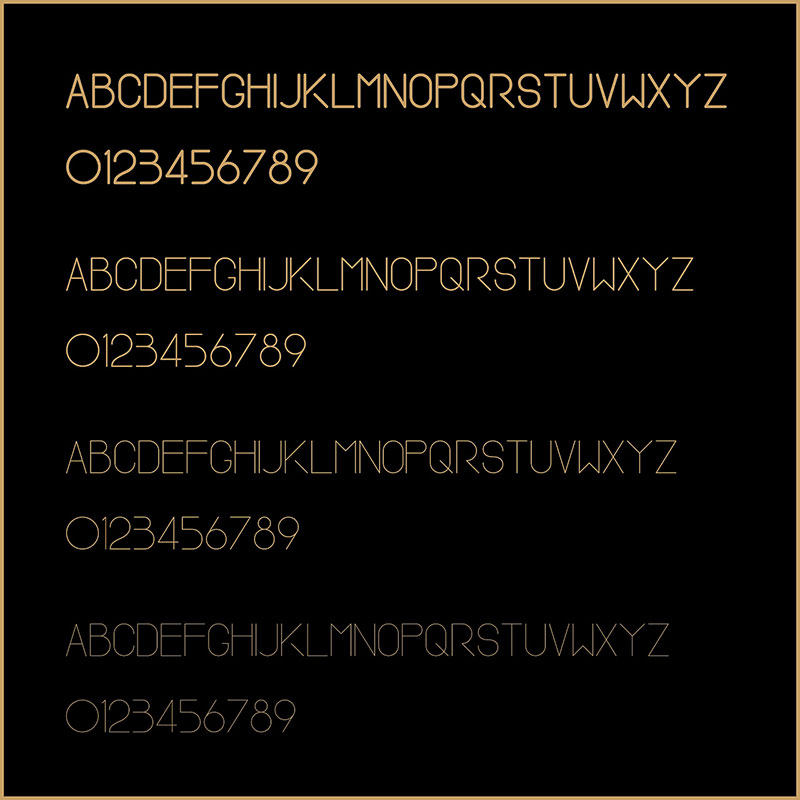
這裡有26(或許×2\(^o^)/)個字母,我們想要設計一款英文字體來自用,於是經過拆解與重構,根據需求與法則,分別做出來這樣26個大、小寫字母,現在放上來與大家共同探討學習下,大家都可以免費下載來使用哦。
原本只打算做26個大寫,後來發現有軟件可以製作成字體安裝包,於是又做出了小寫和數字,但是由於做成字體安裝包比較不順利(剛開始還以為自己學會了新的技能,後來發現想多了),所以我們就一直放著,然後得空就拿出來用PC和MAC不同的字體制作軟件來優化下,而導出總是會出現各種問題,就廢了差不多2個月才拿出來見人,當然現在還是有問題,但是太費時間,所以暫時就先不調整了,一般使用或是作為標題使用還是不錯的。